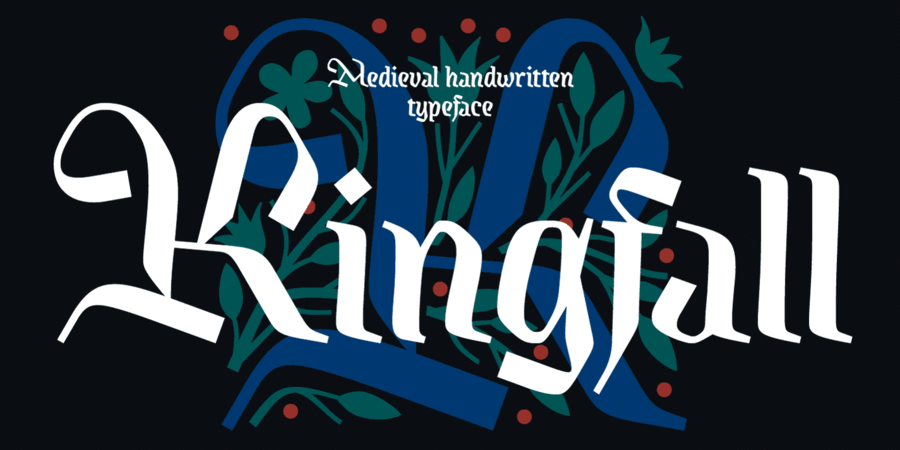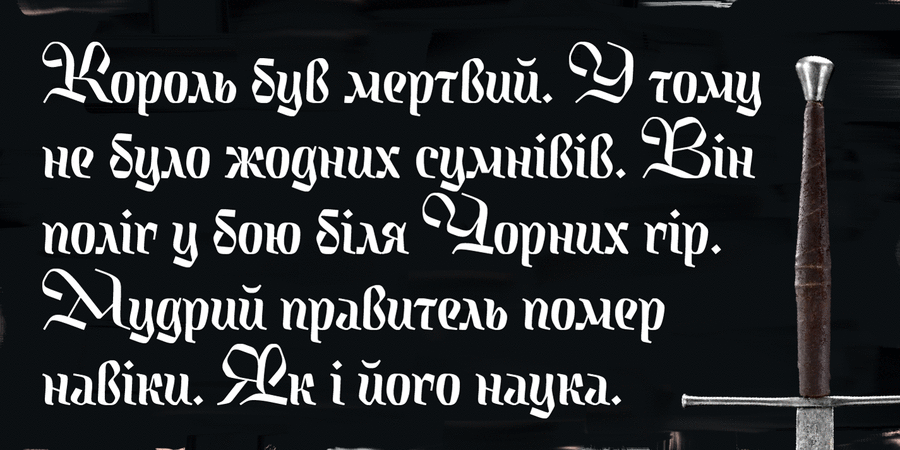
Kingfall це рукописний середньовічний шрифт, виконаний пласким каліграфічним пером. Його дизайн побудований на контрасті вузьких малих літер та широких декоративних великих літер, які також можуть виконувати функцію ініціалів. Форма літер має чисельні грубі злами та жорсткі грані, нібито королівський коваль взяв штабу заліза та формував її молотом. В той же час напрям штрихів уникає геометричної прямолінійності, що додає формі людської дотичності. Шрифтова родина представлена оптичними розмірами: висококонтрастний “Blessed” для заголовків, та середньоконтрастний “Dark” для тексту дрібного розміру. Шрифт розробив Михайло Рафайлик у 2024 році.
Стилі: Aerial, Light, Blessed, Dark, Engraved, Initials. OpenType Features: Initials: Kingfall Initials – стиль шрифтової родини, що включає в себе декоративні версії великих літер – Ініціалів. Шрифт розробив Михайло Рафайлик у 2024 році. Світ ловив мене, та не спіймав!